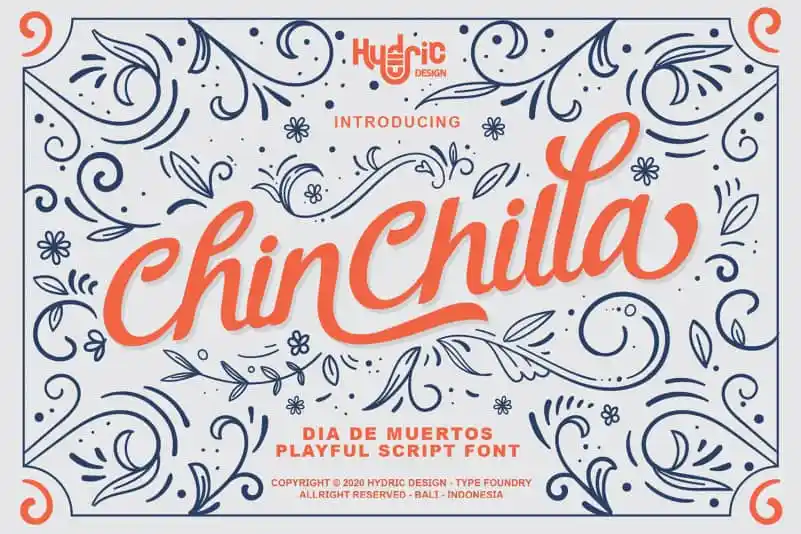
Chinchilla Script Font – Download Grátis
Chinchilla Script Font é uma elegante fonte criada pela HydricDesign inspirada no Dia dos Mortos, um importante festival mexicano que celebra a memória dos entes queridos falecidos durante todo o país de forma mágica e colorida. Seu traço fluido evoca as letras escritas à mão com delicadeza durante este evento cultural único, oferecendo uma experiência visual única para designers que buscam adicionar um toque especial a seus projetos digitais. A fonte Chinchilla Script é especialmente adequada para design gráfico de alta qualidade, como cartazes, revistas e sites. Seu estilo fluido e suave dá aos textos um encanto arquitetônico distintivo, tornando a experiência do usuário em experiências de interação mais envolventes. A HydricDesign não apenas inspira a criatividade dos designers, mas também ajuda-os a criar projetos que se destacam e cativam o público. Chinchilla Script, então, é uma fonte que traz o encanto mágico do Dia dos Mortos diretamente para os designers digitais. Seu estilo fluido e versátil oferece um jeito inovador de experimentar a beleza da cultura mexicana através das letras, tornando-a uma escolha natural para qualquer projeto que busque agregar um charme especial ao seu design.